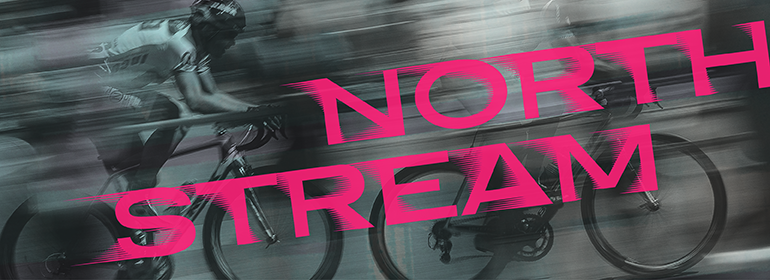
Northstream Wind™
Northstream Wind™,这款字体结构工整、笔画清晰,兼顾美观与易读性,适用于标题、正文、海报、包装、LOGO 等多种场景。字形优雅稳定,风格百搭耐看,适配日常排版与创意设计,让文字呈现更舒适、更具质感。Northstream Wind™一笔一画,皆是细节,以均衡的比例、流畅的线条打造舒适视觉体验,字形端正大气,风格简约现代。无论是商业设计、品牌宣传还是日常排版,都能轻松驾驭,让文字更有格调与力量。Northstream Wind™字体下载。